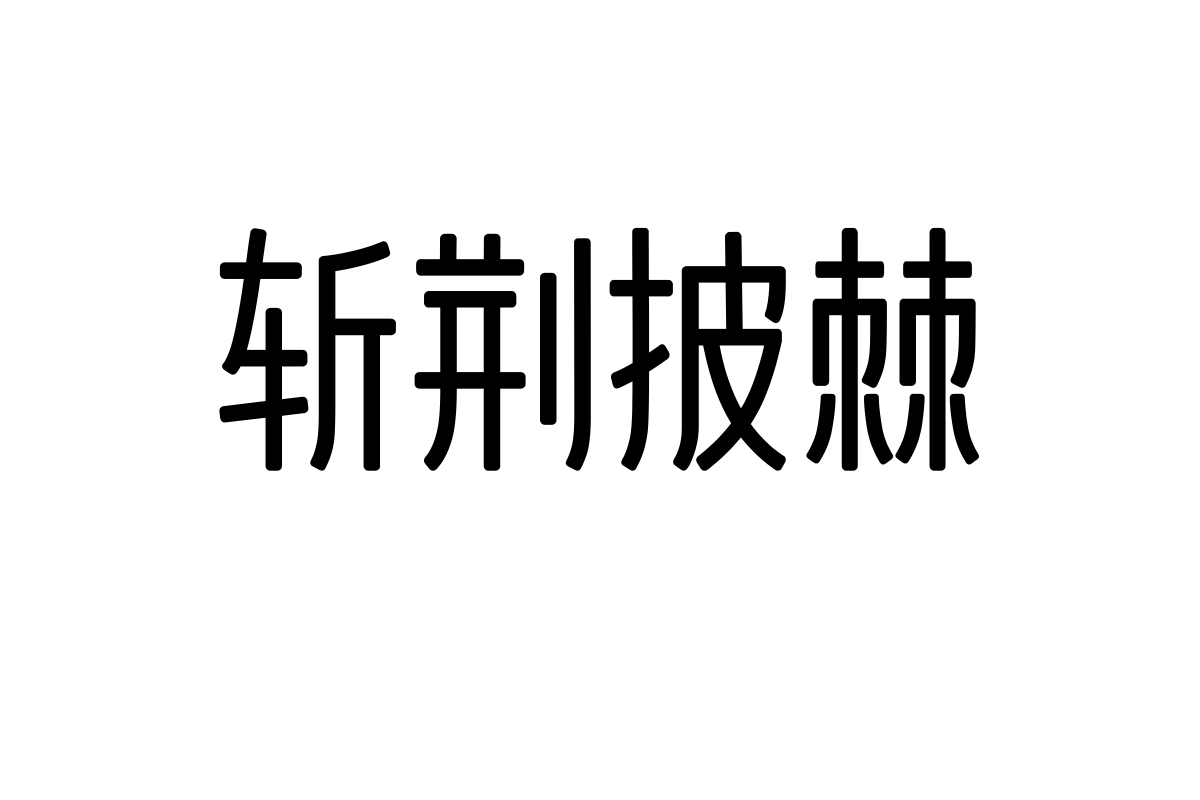
上首悦风体是一款具有独特风格的中文字体,其特点是笔画流畅、结构紧凑、字形优美。这款字体适合用于各种需要展示文字美感的场合,如广告设计、海报制作、网页设计等。
上首悦风体的设计理念是追求简洁、明快、易读性高的文字风格。在字形上,它采用了现代的设计手法,使得每个字都显得生动活泼,富有个性。同时,上首悦风体也注重文字的可读性,通过合理的间距和行距,使得文字在视觉上不会过于拥挤,易于阅读。
上首悦风体的应用场景非常广泛,无论是在传统的印刷媒体还是现代的数字媒体中,都能展现出其独特的魅力。例如,在报纸、杂志的广告设计中,上首悦风体能够很好地传达出品牌的形象和信息;在网站和APP的设计中,它也能为界面增添一份灵动和活力。
总的来说,上首悦风体是一款非常适合现代设计需求的文字字体,无论是从美观度还是实用性方面,都能满足用户的需求。